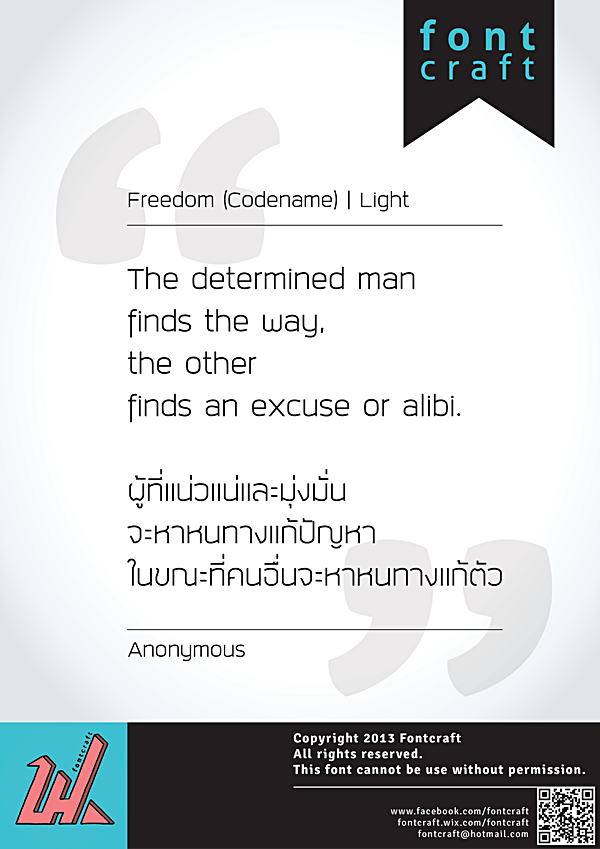
เนื่องจากช่วงนี้เห็นหลายๆ ท่านสร้างสรรค์ฟอนต์ที่เรียบร้อย สวยงามเป็นจำนวนมาก
เลยขออนุญาตเอางานเก่ามาโชว์ตัวกันบ้างครับ
เริ่มกันที่ตัวแรก Freedom สร้างสรรค์ขึ้นมานานตั้งแต่ต้นปี มี 3 น้ำหนักให้เลือกใช้
ตอนแรกตั้งใจว่าจะขายขาดให้กับองค์กร แต่ทว่าจนถึงตอนนี้ก็ยังขายไม่ออก T T
ได้เวลาปัดฝุ่นเอามาโชว์ตัวกันหน่อยครับ
รู้สึกว่าพอ Resize รูปแล้วทำไมตัวอักษรดูไม่ค่อยชัดเลยหว่าาา
ตัวต่อไป Line เป็นฟอนต์ที่ทำแบบง่ายๆ ปั่นจบใน 1 วัน
ตัวไทยดูเป็นเหลี่ยมๆ เข้าชุดกันดี ตัวละตินดูมนๆ เข้าชุดกันดีเช่นกัน
แต่พอเอามารวมเป็นฟอนต์เดียวกัน รู้สึกว่ามันไปด้วยกันไม่ได้แฮะ  :08: ก้อเลยดองยาว ยังไม่ได้แก้เพิ่มเติมแต่อย่างใด
ตัวที่สาม Waffle เป็นฟอนต์ลายมือน่ารักๆ ซึ่งทำให้กับ www.fb.com/wafflevest
โดยผู้จ้างวานตั้งใจจะแจกจ่ายฟรีอยู่แล้ว ตอนแรกตั้งใจไว้ส่งเสริมการขาย แต่ปัจจุบันปล่อยให้ดาวน์โหลดได้ฟรีเลย  :33: